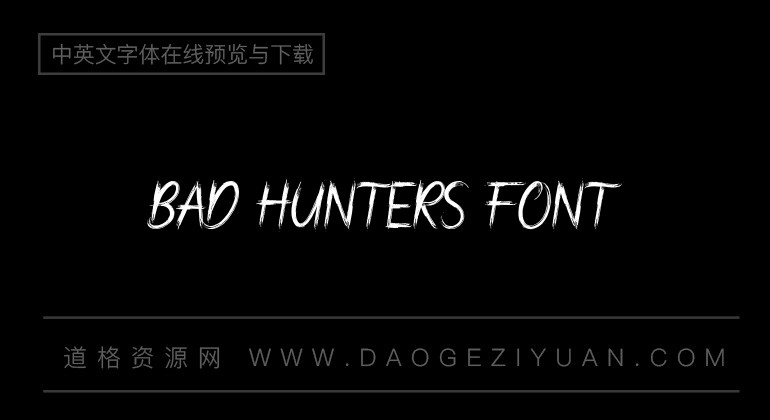
Bad Hunters Font
Bad Hunters Font 是一种手写风格的字体,它的设计师是名叫 Tano Veron 的图形设计师。 这个字体的风格非常适合用于户外、野生、探险、野营等主题的设计,因为它看起来像是用粗笔创作的手写字体,充满了粗犷和野性的气息。 Bad Hunters Font 的字母都是大写字母,每个字母都有一些装饰性的元素,例如在字母“B”和“R”上,有一个类似锯齿状的线条,这些装饰元素让这个字体看起来更加有特点和个性。 这个字体有两种字重可供选择:正常和粗体,而且它还包含了一些特殊字符,例如 @、#、$ 等符号,以及数字。Bad Hunters Font 可以用于很多不同的设计项目中,例如海报、标志、名片、网页设计等,为设计师们带来了非常多的便利。
Bad Hunters Font是一款非常不错的手写艺术字体,具有很好的视觉感,适合于文化类的宣传设计、商业类品牌的广告和产品包装设计以及个性化文字排版等较多场景。